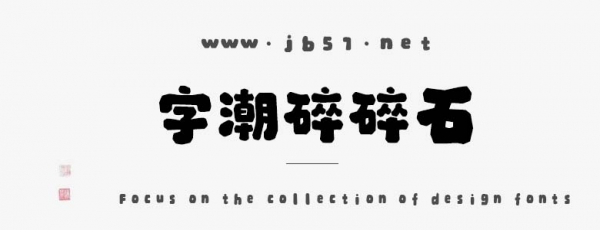
字潮碎碎石是由字潮字庫(kù)出品的字體,這款字體筆觸略粗,字形圓潤(rùn),略顯可愛,具有很好的視覺感,適合應(yīng)用于藝術(shù)設(shè)計(jì)、平面宣傳設(shè)計(jì)、網(wǎng)頁(yè)設(shè)計(jì),書法字帖等領(lǐng)域,需要的朋友可以前來(lái)本站下載。